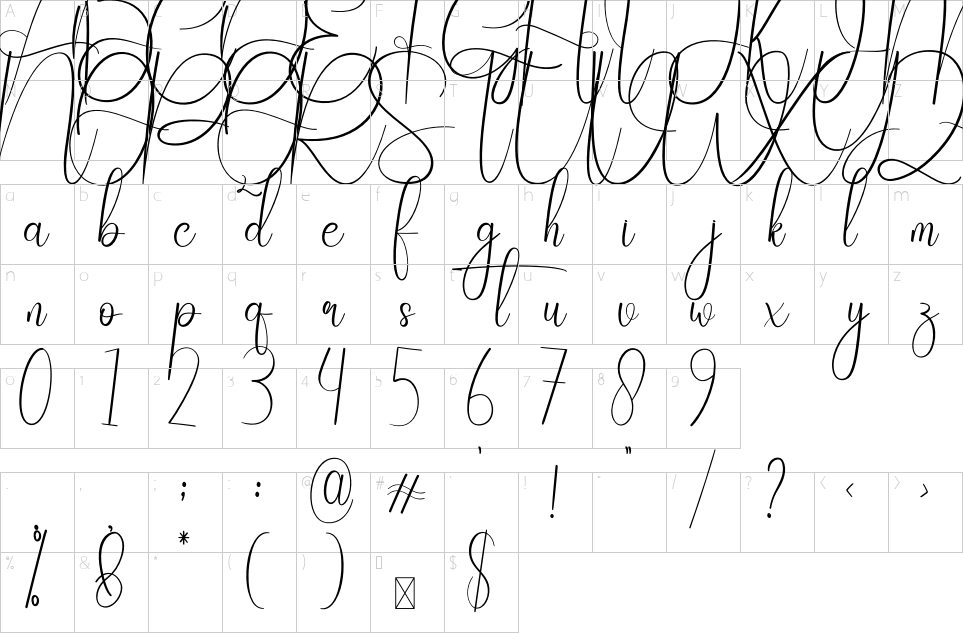
Anastasia Font – Download Grátis
Anastasia é uma fonte elegante e moderna, ideal para quem busca um equilíbrio entre elegância e simplicidade. Suas linhas finas e acentos delicados garantem um estilo moderno que se adapta perfeitamente a uma vasta gama de aplicativos, desde editoras de texto até sites de design. Este é um tipo de fonte clean que se destaca por sua capacidade de transmitir uma mensagem clara, tornando-o perfeito para textos que precisam de uma aparência suave e sofisticada. Desenvolvida por um designer não especificado, Anastasia foi uma escolha popular, sendo baixada 685 vezes, indicando sua valorização por designers e profissionais de design. Seja para criar cartazes, logotipos, ou simplesmente uma fonte para seus documentos de trabalho, Anastasia é uma opção confiável que certamente irá deixar seu design mais profissional e atraente.